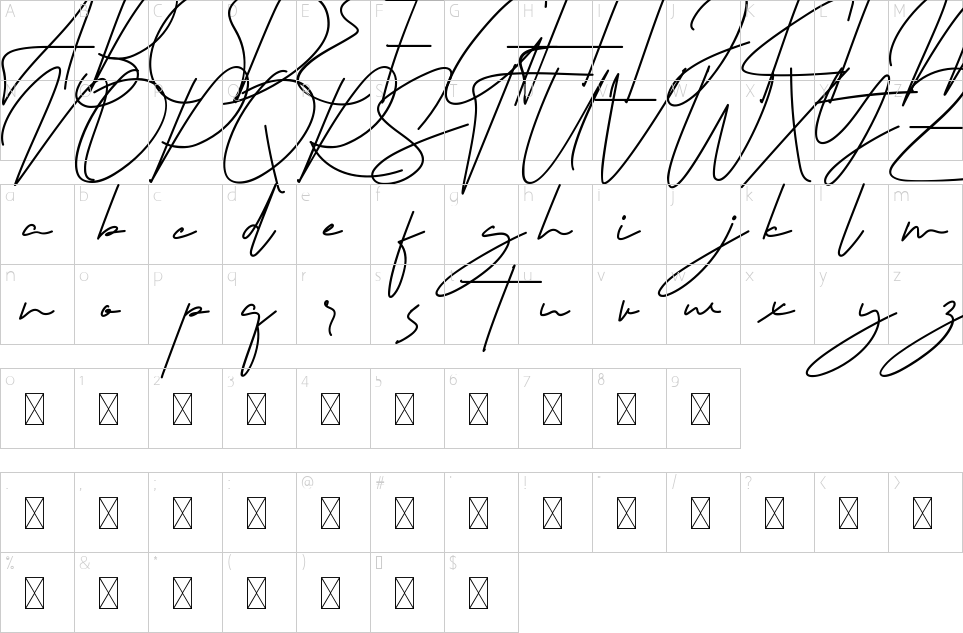
Descubra a beleza da Signaturex, uma fonte única e elegante disponível para você gratuitamente. Desenvolvida pela equipe do nihstudio, esta fonte foi projetada com um toque moderno e criativo, adequado para diversos estilos de design. Com seu design minimalista e fluido, a Signaturex se adapta perfeitamente tanto em textos legíveis quanto em gráficos e logotipos, proporcionando uma variedade impressionante de opções. Seja você um designer ou ilustrador, a Signaturex oferece o que há de melhor em fontes sem pagar nada pelo uso. Até o momento, ela já foi baixada mais de 7,646 vezes, demonstrando seu grande potencial e popularidade no design digital. Instale-a agora e experimente essa fonte para enriquecer suas criações visuais.